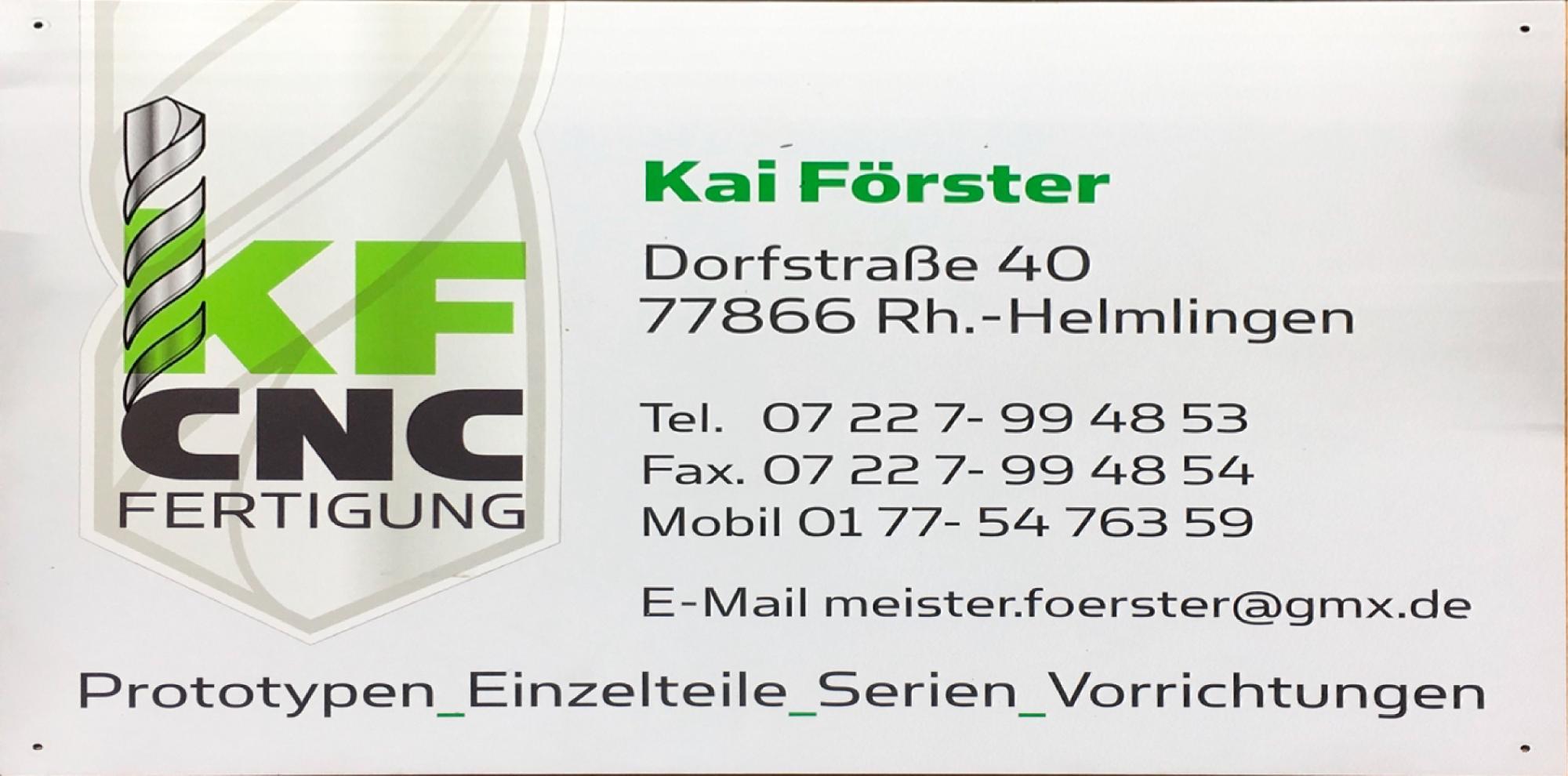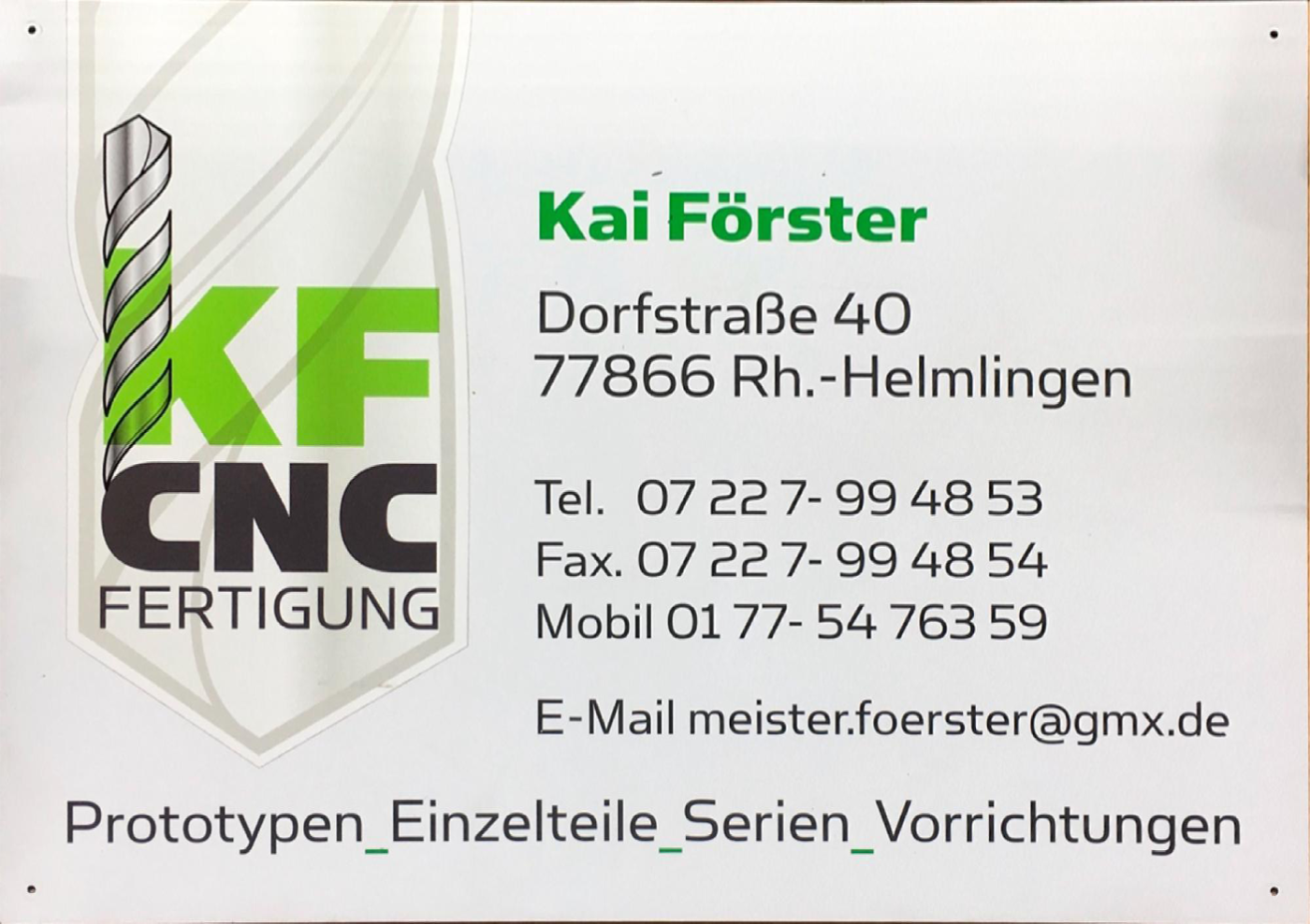
Schriftart gesucht. Kennt jemand diese Schrift oder ist sie aus mehreren Schriften zusammengesetzt? (KF CNC)
ich soll für meinen Onkel ein Schild erstellen. Leider finde ich die Schrift nicht. Könnte die Schrift aus mehreren Schriften zusammengestellt sein?
Ich vermute, dass sie horizontal auf 150–200 % gestreckt wurde.
Kann aber auch teilweise vom Foto kommen. Kennen Sie zufällig die Schrift? Ich denke das S und die 2 sind ja schon speziell, aber ich finde leider nichts bei dem der Rest auch passt.